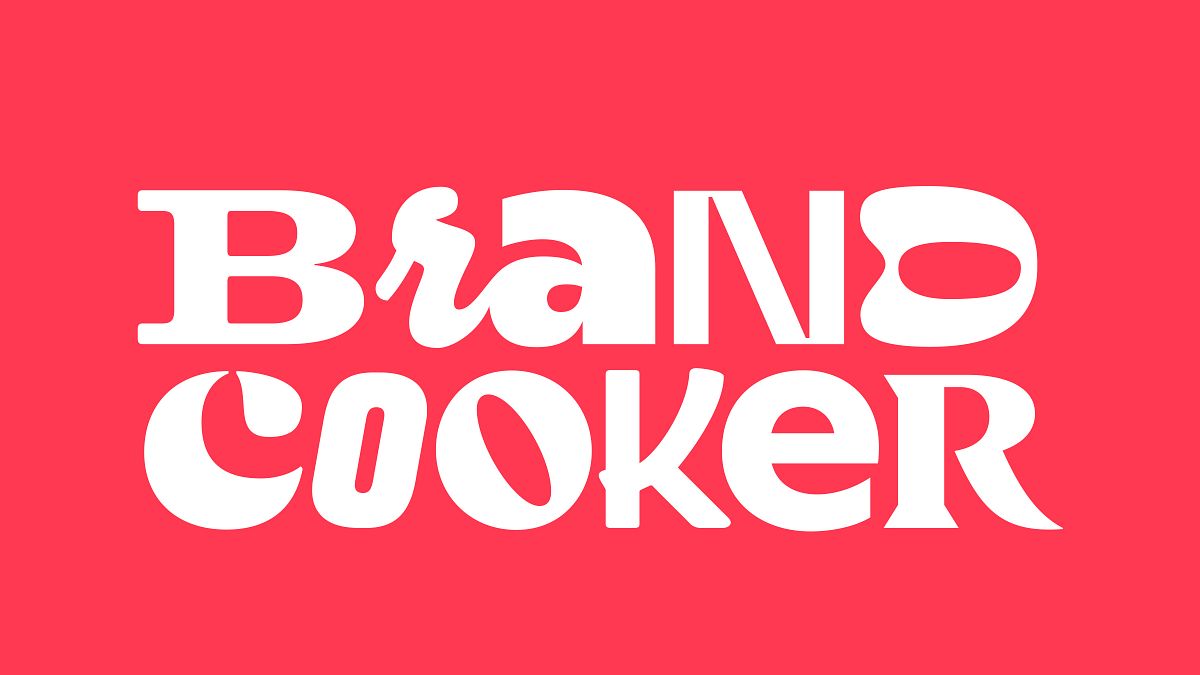
Desvelando el Poder de las Letras: Cómo Crear Logotipos y Tipografías que Cuentan Historias
Como diseñadores apasionados por el universo de las letras, nosotros en el Estudio Plau, Rodrigo Saiani y Carlos Mignot, vivimos a diario el desafío y la belleza de crear tipografías que no solo comunican, sino que también encantan. Crear una tipografía o un logotipo va mucho más allá de simplemente dibujar letras; es sobre transcribir la esencia de una marca, su personalidad y valores, en formas visuales que hablan directamente al corazón de sus consumidores. ¡Queremos hacer tipografía pop!
Al iniciar un proyecto de tipografía, es crucial tener en mente no solo la estética, sino también el modelo de negocio de la empresa. Siempre nos preguntamos: "¿Este diseño refleja la naturaleza de la empresa?". La respuesta a esta pregunta guía nuestro proceso creativo, asegurando que el logotipo represente adecuadamente el espíritu de la marca.
La comparación con la competencia también es una etapa indispensable. Analizamos cómo podemos diferenciar la marca, haciéndola única en un mar de semejantes. Un logotipo que identifica claramente a la empresa y la diferencia de los competidores es esencial para destacarse en el mercado.
Incorporar un elemento de sorpresa en el diseño puede transformar la manera como el público interactúa con el logotipo. Un momento de descubrimiento crea un vínculo más profundo con la marca, haciendo la experiencia más personal y memorable.
La atemporalidad es otra consideración vital. Nos preguntamos: "¿El diseño será efectivo y relevante dentro de 10 años?". Evitamos símbolos muy comunes que pueden diluir la fuerza del logotipo, buscando un equilibrio entre originalidad y relevancia duradera.
La perspectiva de Doyald Young sobre la importancia de dibujar letras desde cero resuena profundamente con nosotros. Creemos en mirar las fuerzas internas de las marcas, explorando su punto de vista único en lugar de solo seguir las tendencias externas. Este proceso nos permite crear logotipos, lettering, fuentes y paletas tipográficas que reflejan con más autenticidad el poder de las marcas.
Queremos ser un contrapunto al movimiento de Branding, donde muchas marcas optan por diseños seguros y genéricos. Abrazamos la expresividad y puntos de vista únicos como nuestro punto de partida.